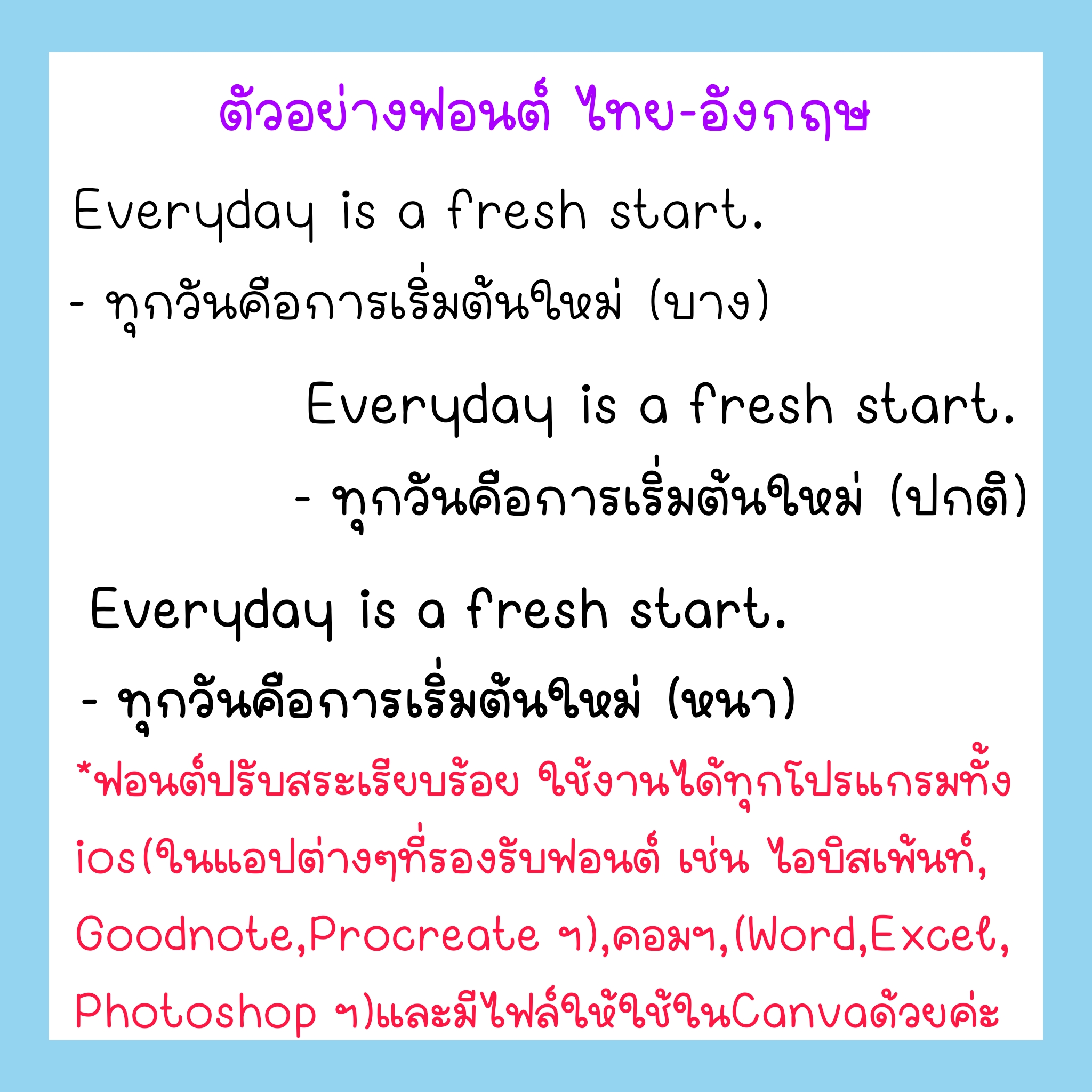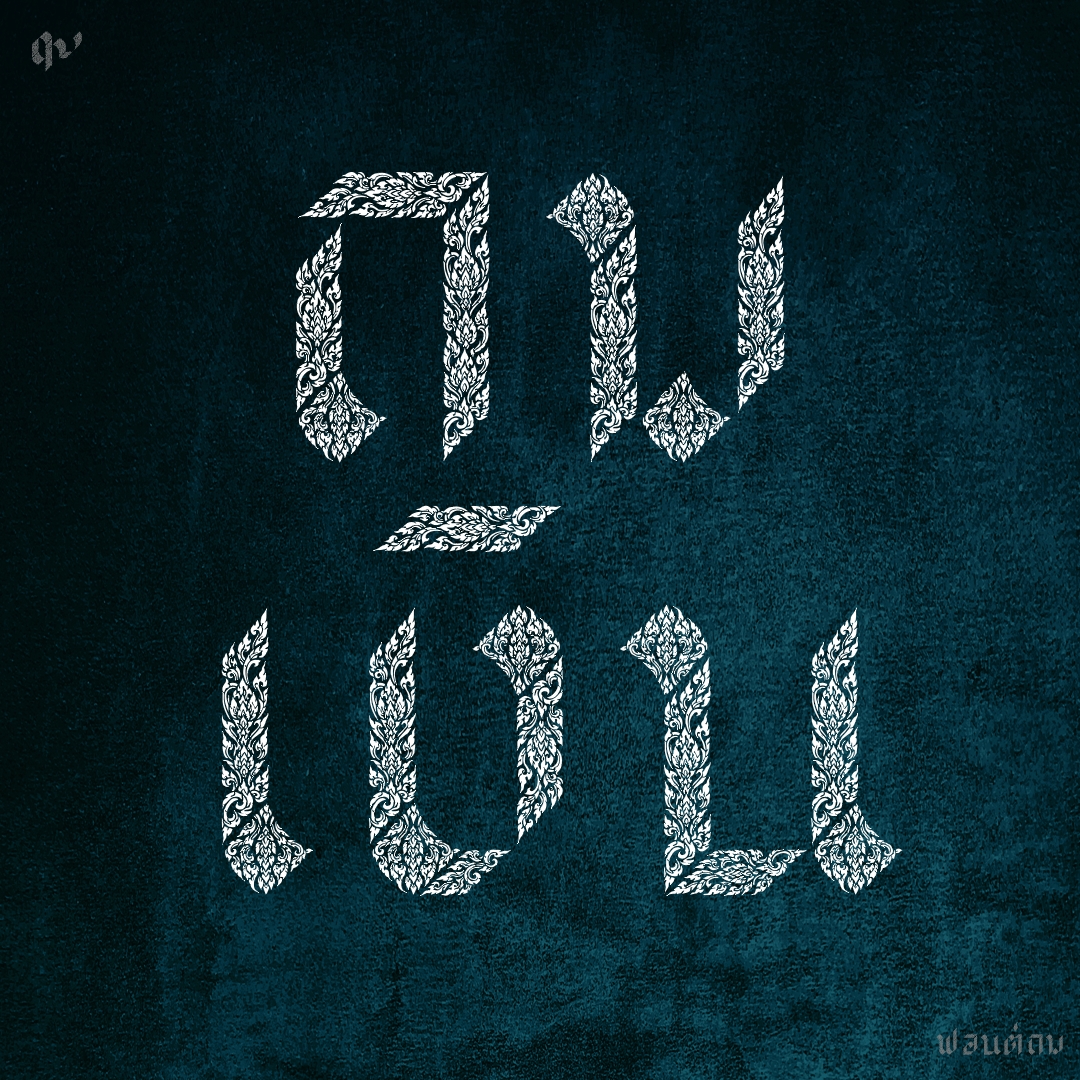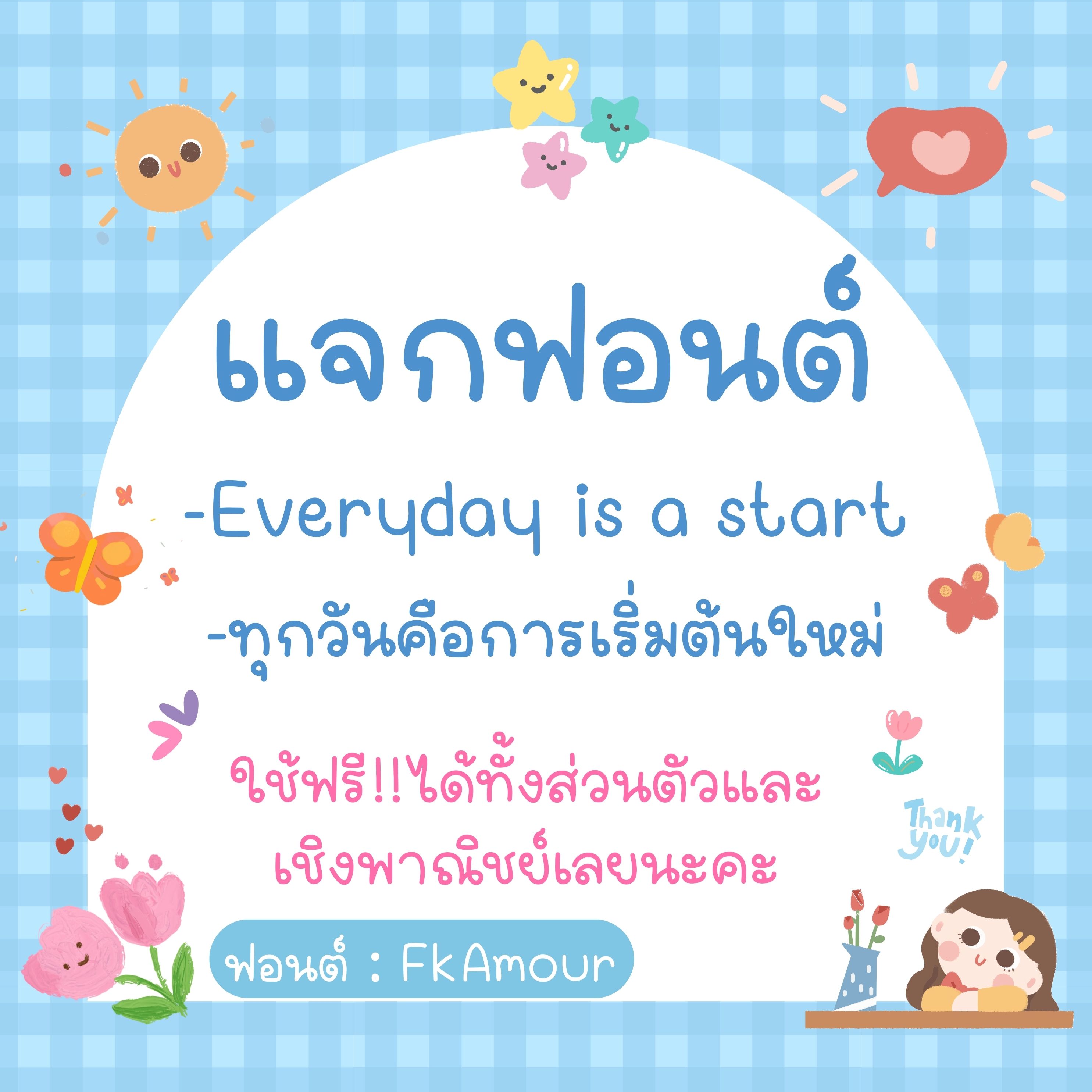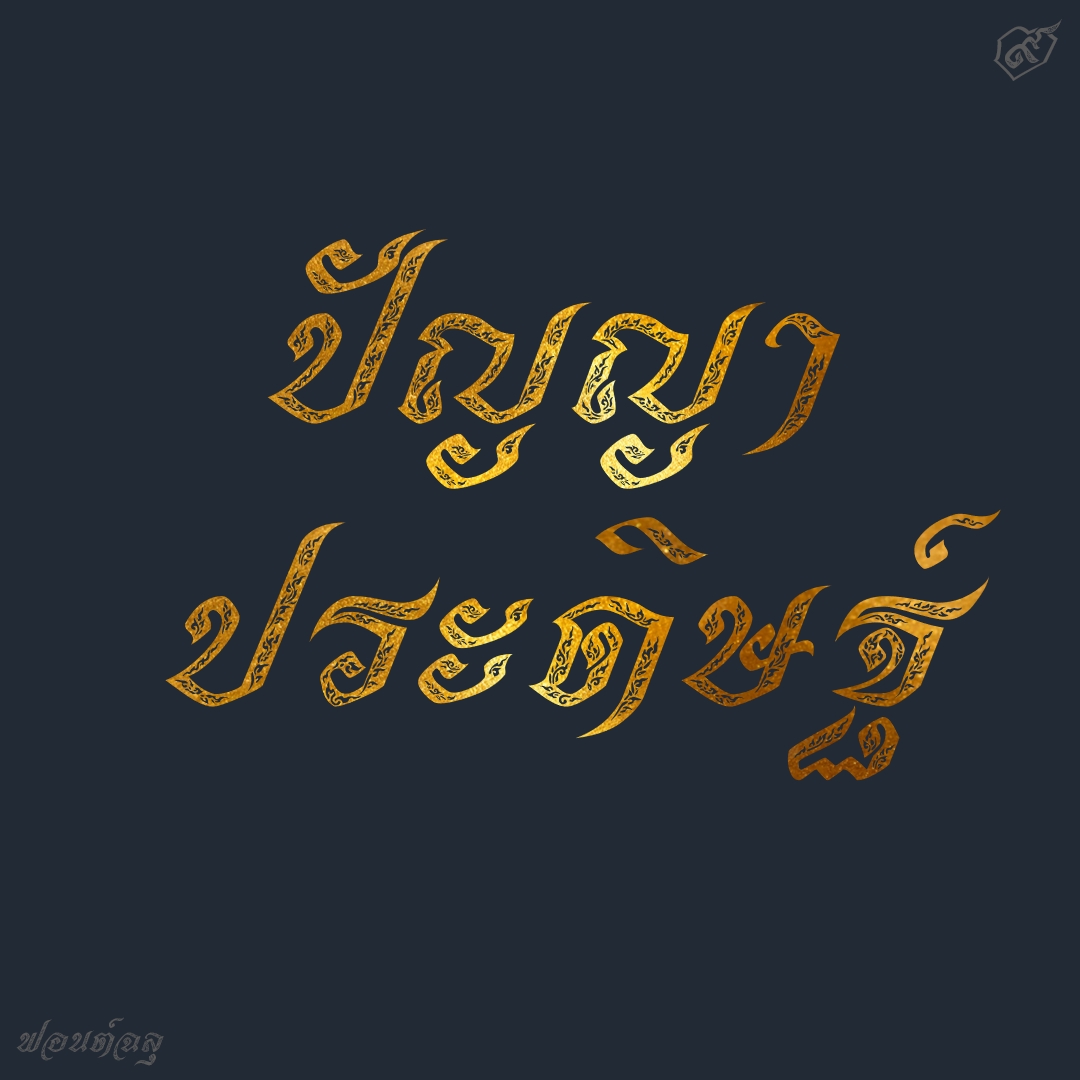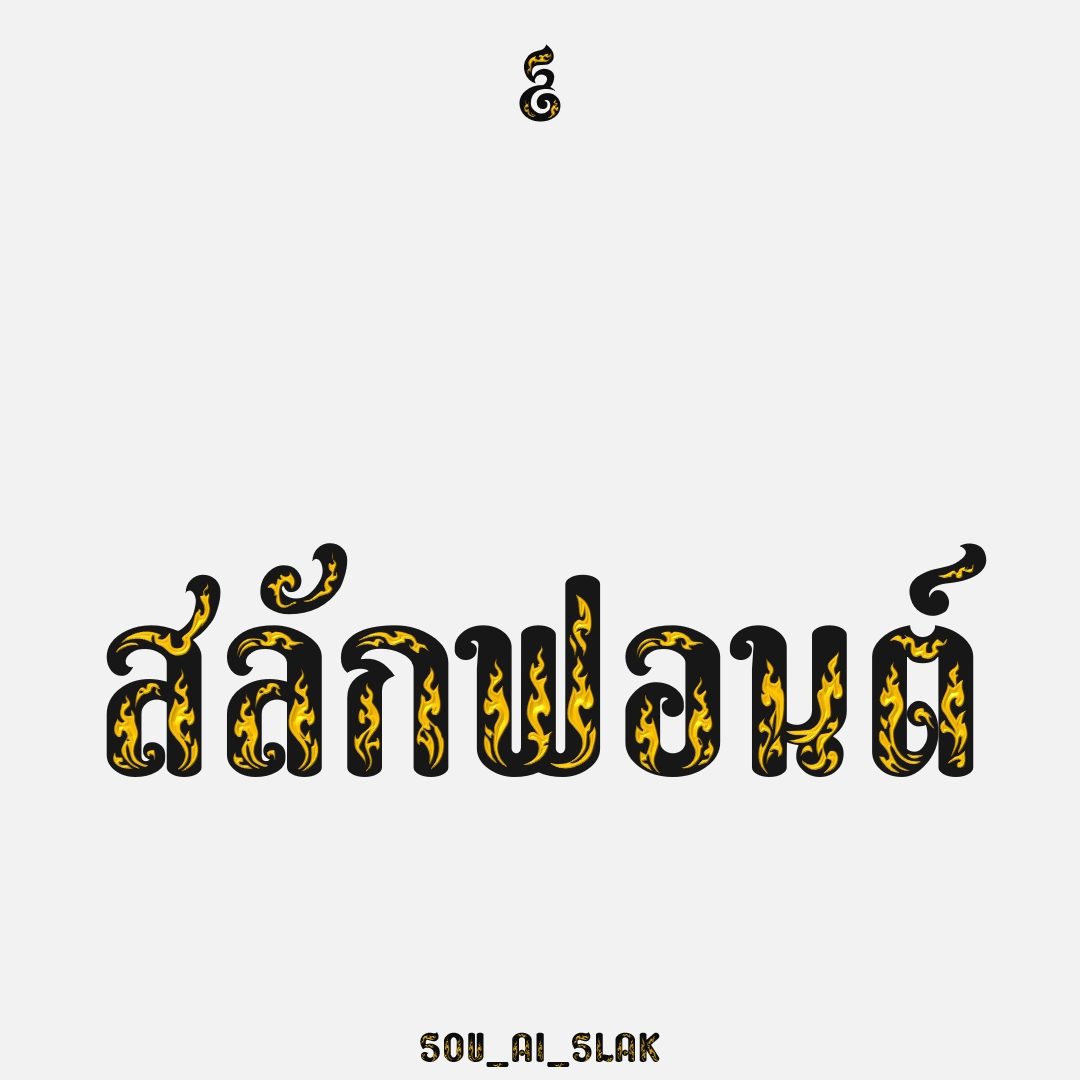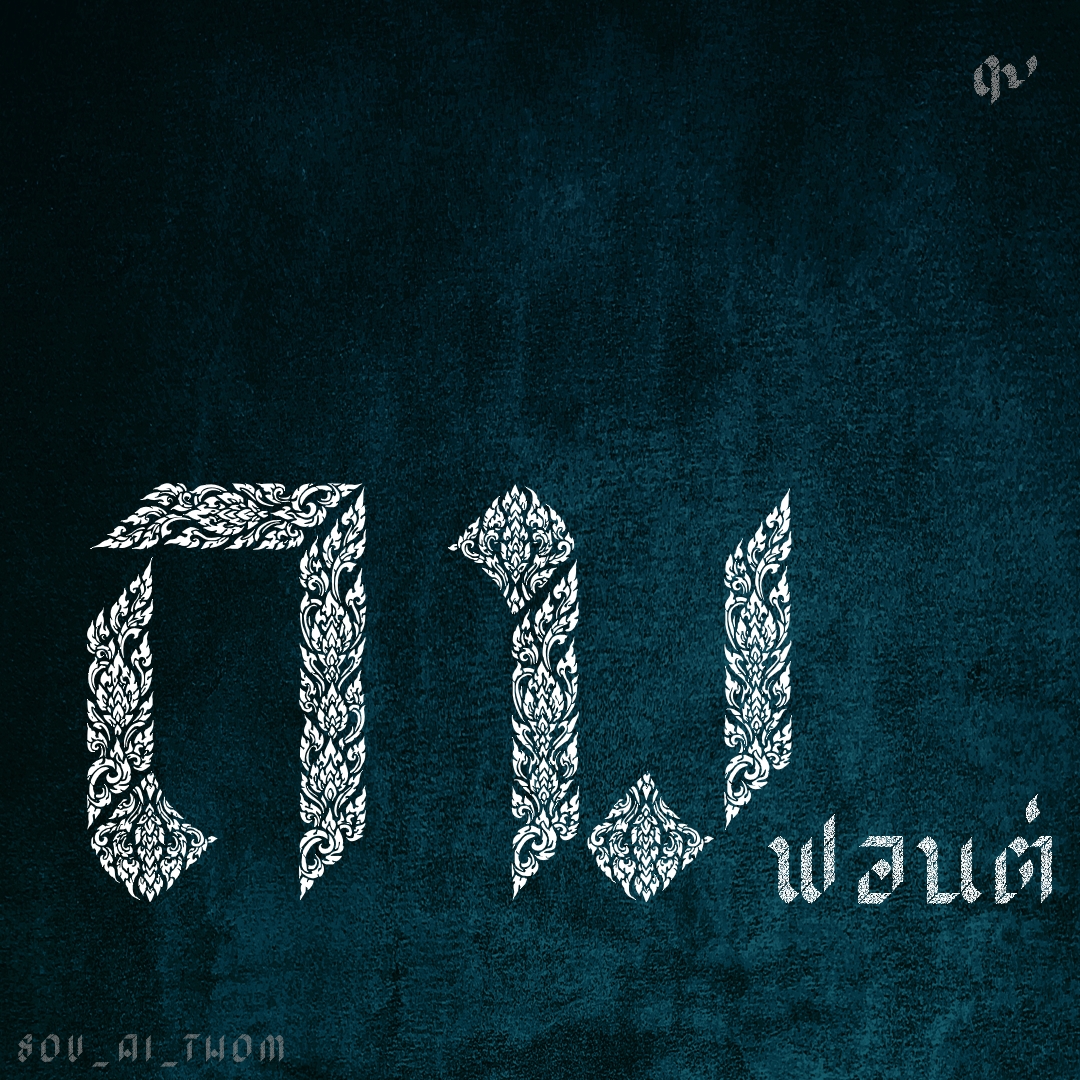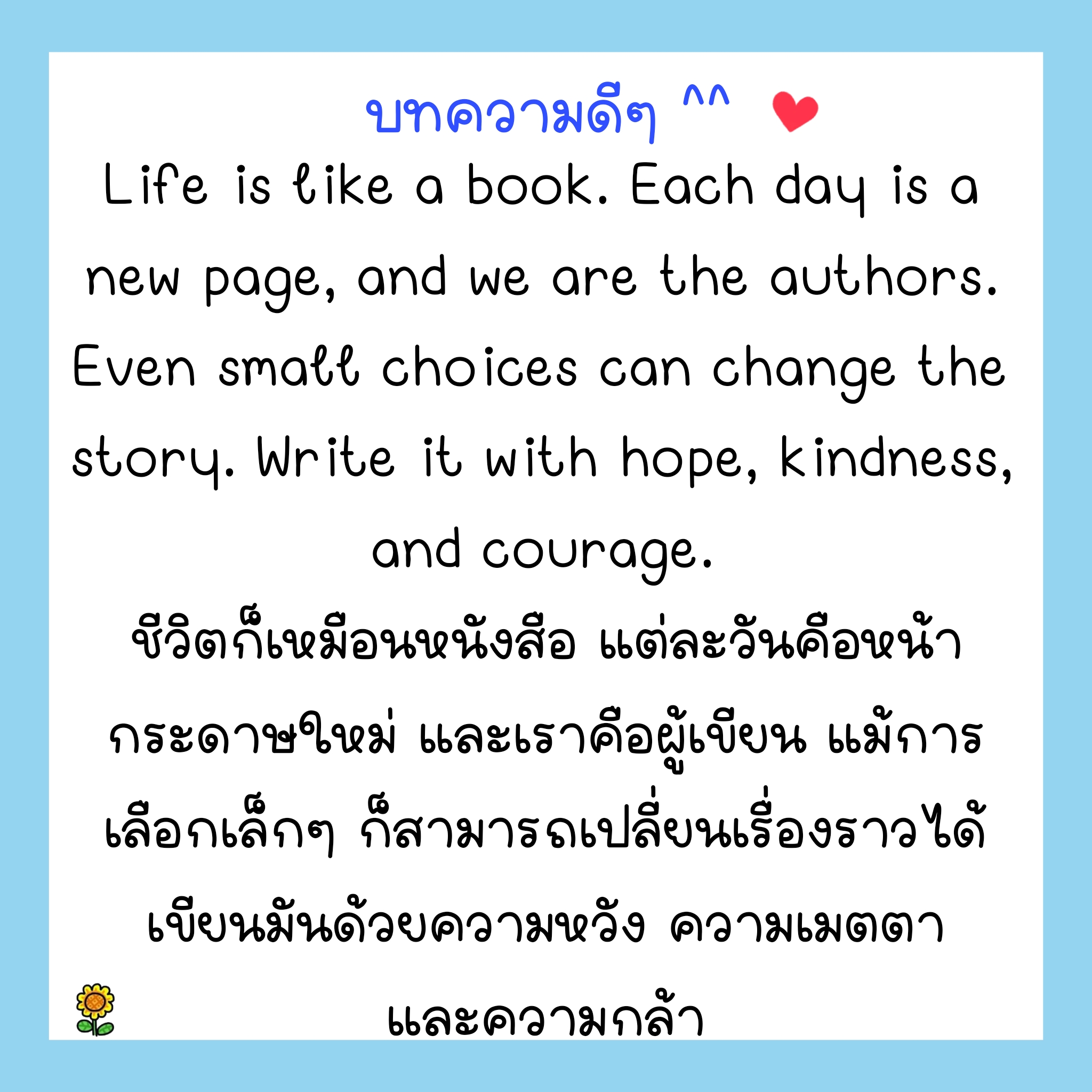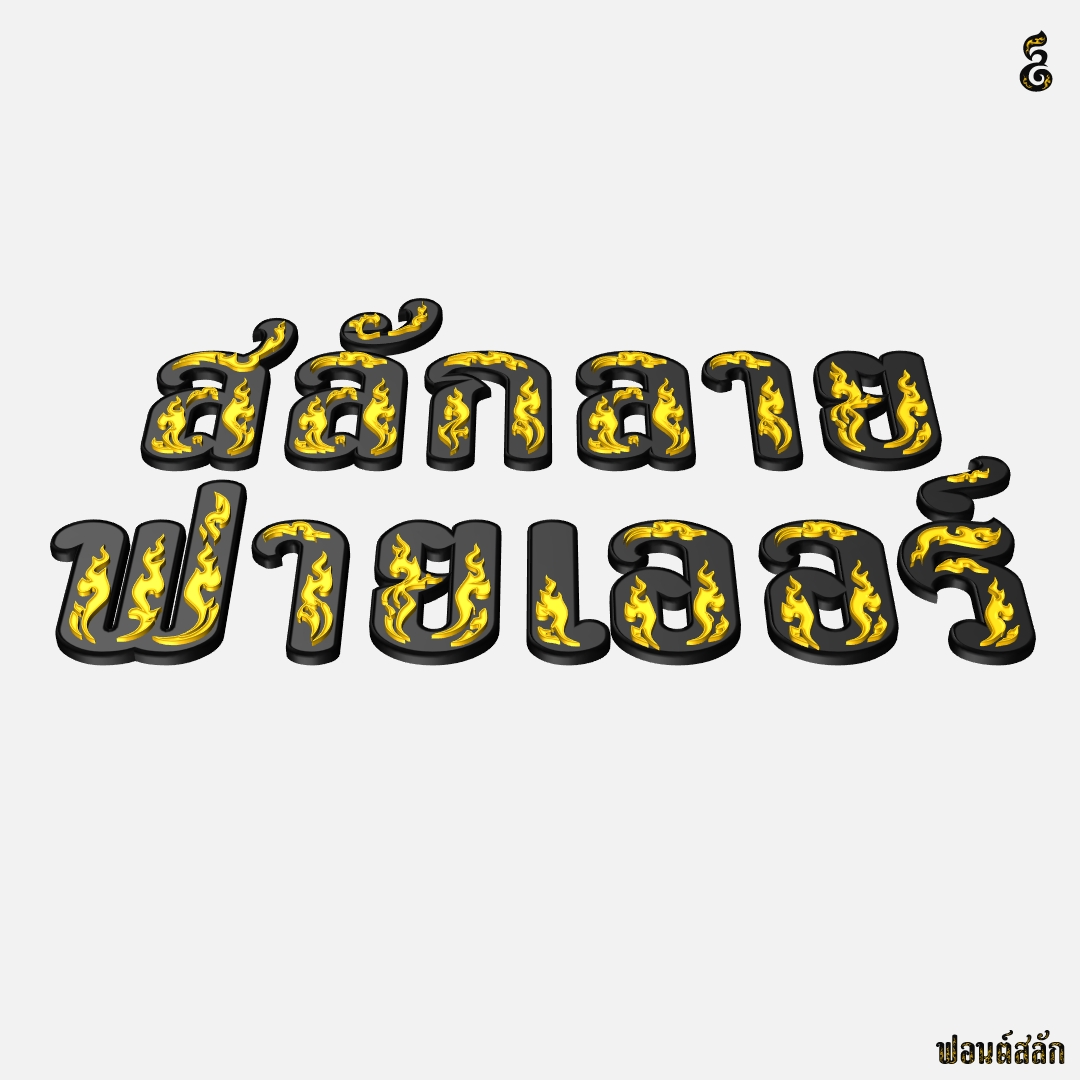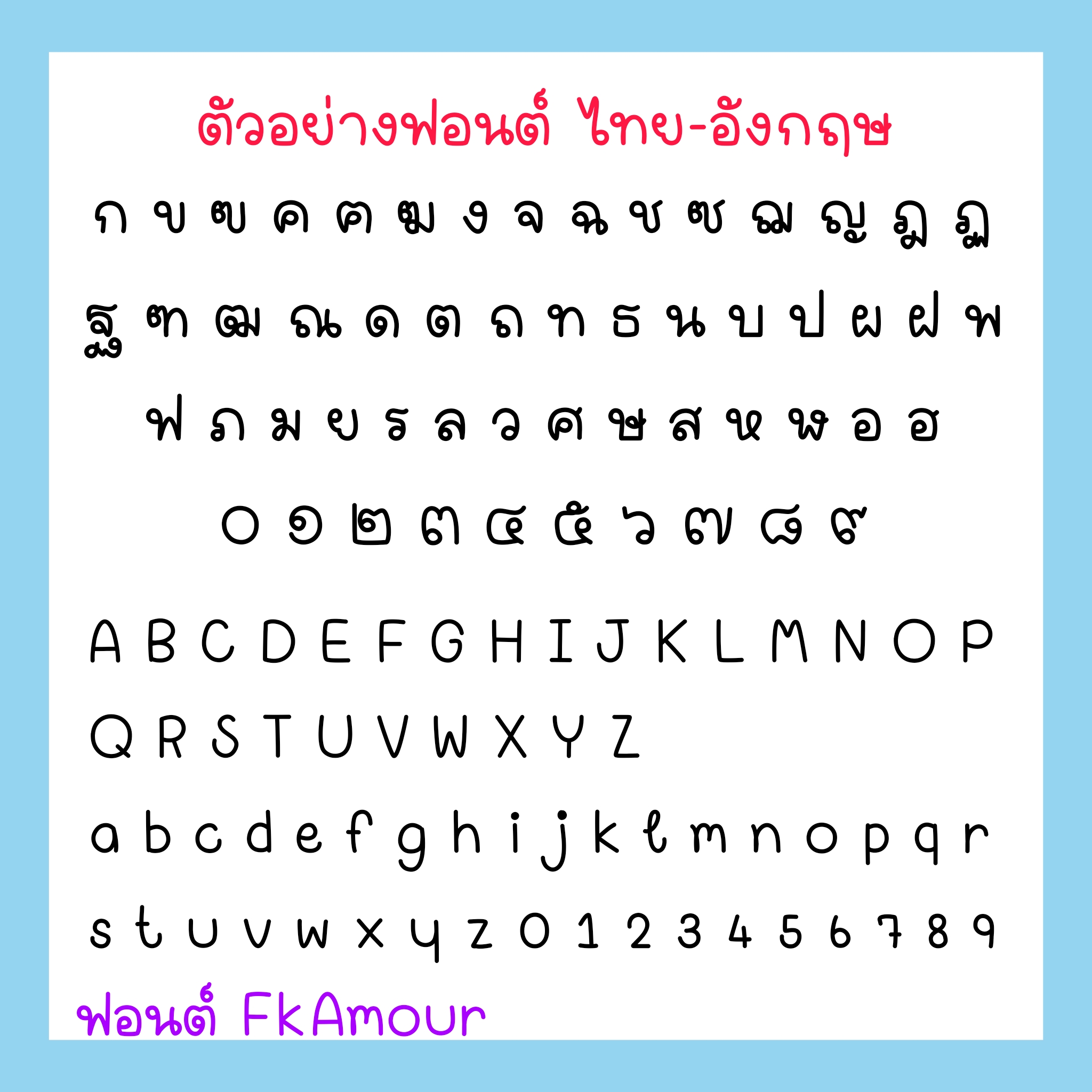
ฟอนต์: ซินแคลร์(TKSinclair)
ชื่อฟอนต์ : ฉลุ
ฉลุ เป็นฟอนต์ทำลองนำ AI มาช่วยออกแบบลาย บนฟอนต์เดิมของเรา..ตะแบงเอียง (SOV_TaBang) แล้วนำลายนั้น ย้อนกลับมาทำเป็นลายฉลุบนฟอนต์อีกที
ชื่อฟอนต์ : สลัก
สลัก ทดลองให้ AI ออกแบบลาย บนฟอนต์ของเราที่มีความกว้างของเส้นอักษร..ฟอนต์ธนบุรี (SOV_ThonBuri) เพื่อให้ได้ลายขนาดใหญ่ สำหรับทำเป็น layer font ซ้อนอยู่บนฟอนต์เดิม สามารถใส่ effect นูน บุ๋ม คล้ายการแกะสลัก ..เวลาใช้งาน พิมพ์ฟอนต์ธนบุรีก่อน จากนั้นทำ layer ใหม่ ซ้อนขึ้นมา แล้วค่อยเปลี่ยนเป็นฟอนต์ตัวนี้ ก่อนตกแต่งต่อไป
แจกฟอนต์จ้า!! ฟอนต์ FkAmour ฟอนต์ลายมือแนวน่ารัก ตัวกลมๆอ่านง่ายสบายตาค่ะ
ฟอนต์หมีบอนนี่ (KMBonnie) โหลดฟรีไฟล์ Demo
ฟอนต์โซฮอล์ (TCS4Sohol)